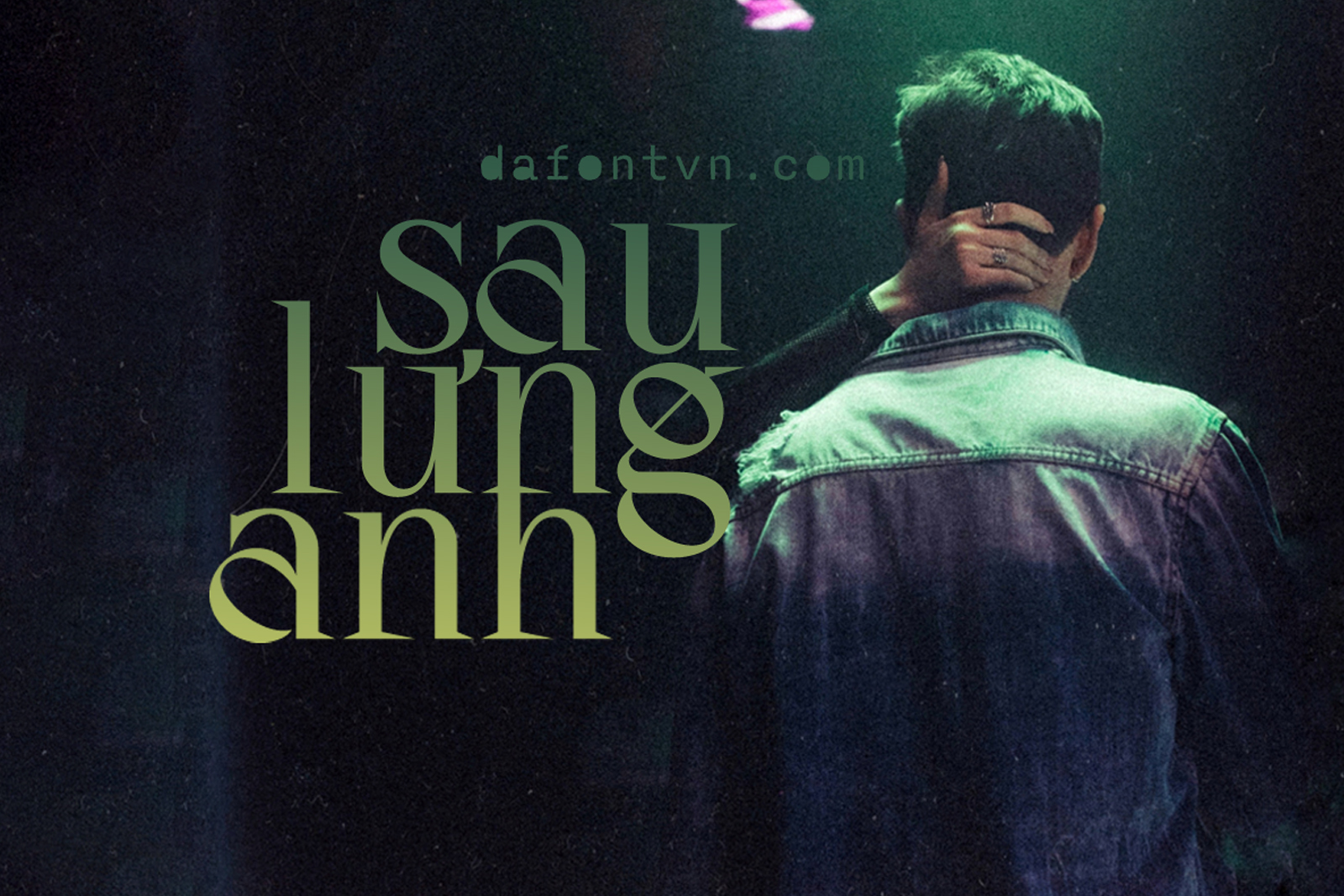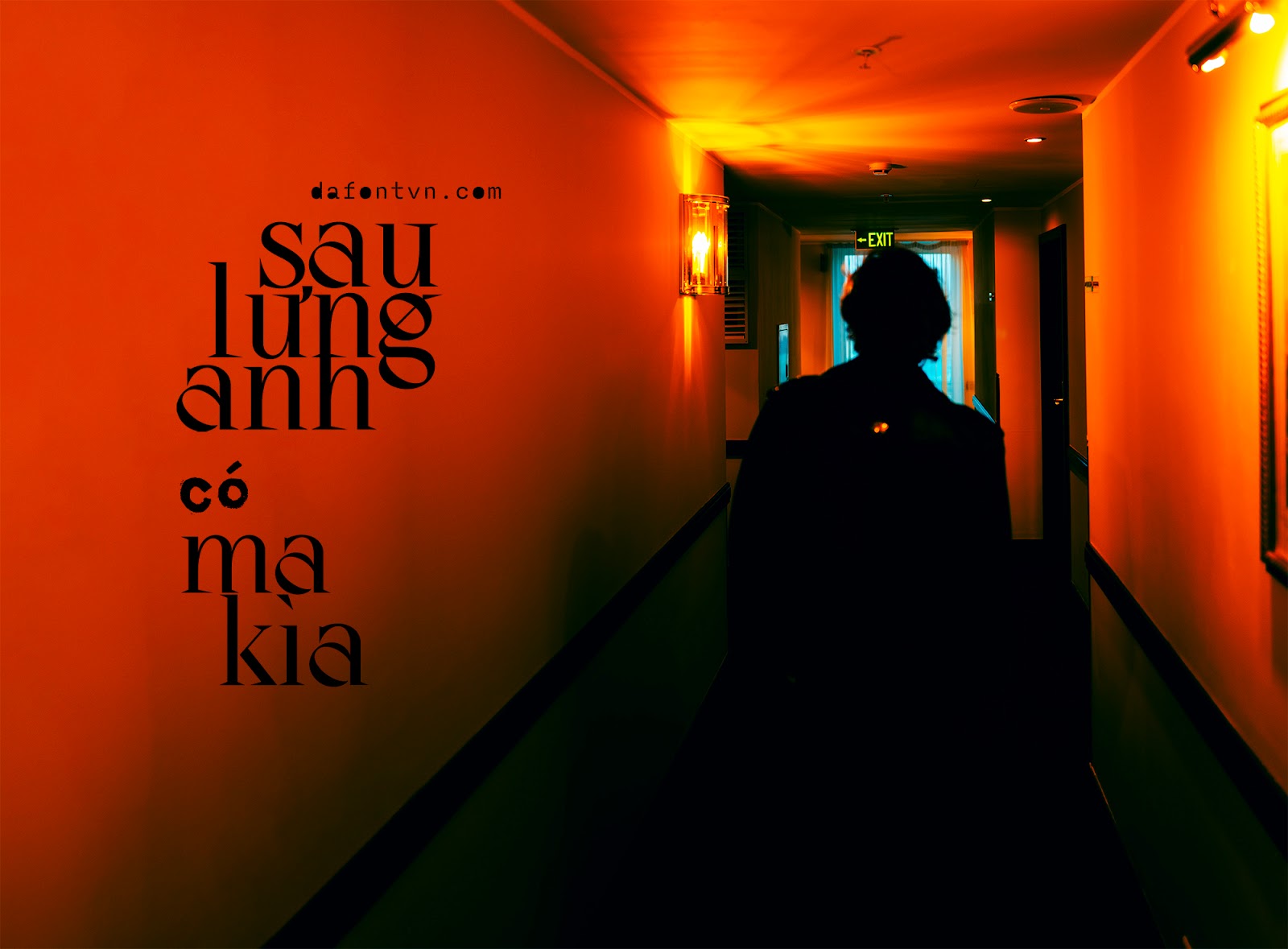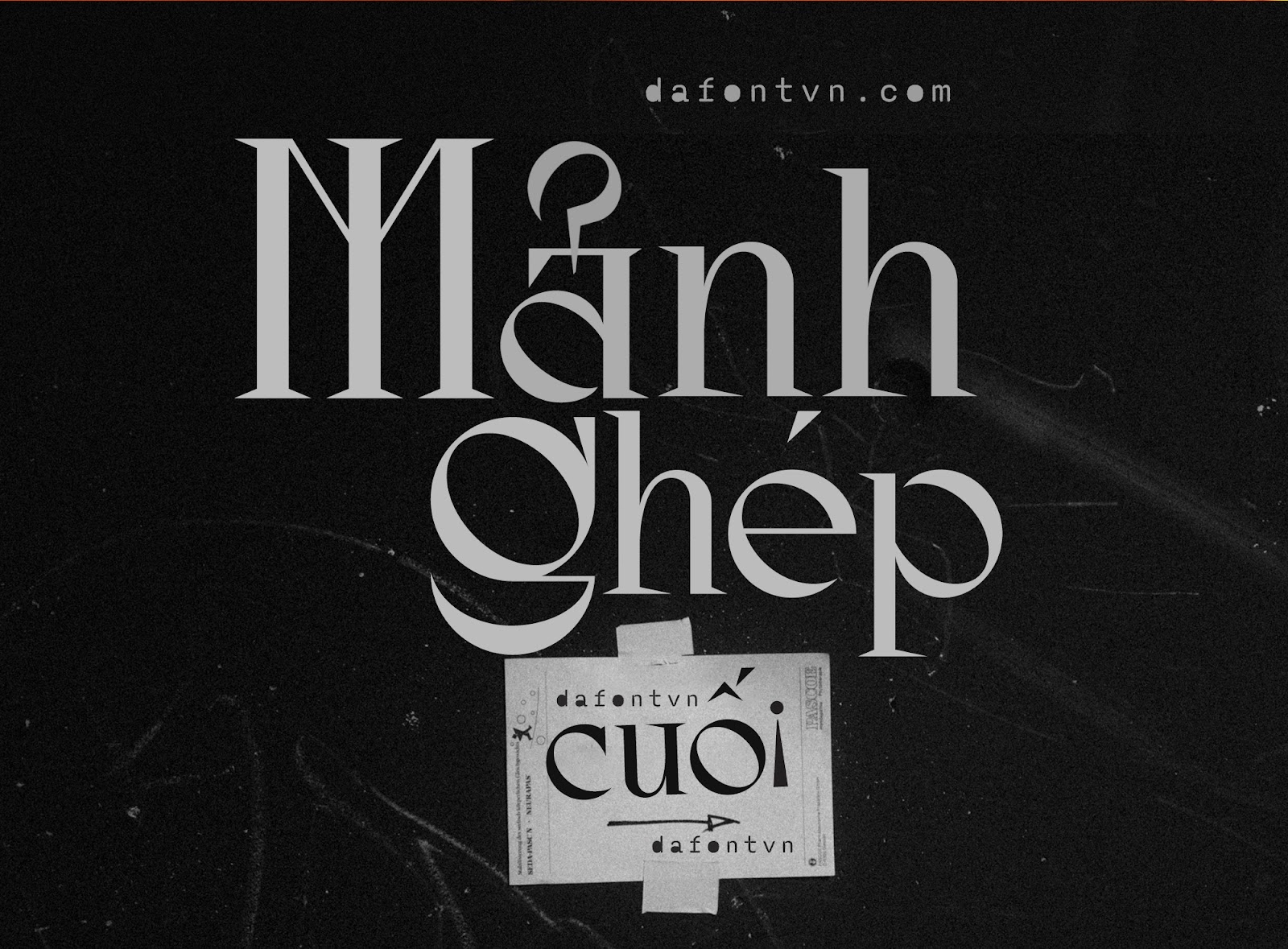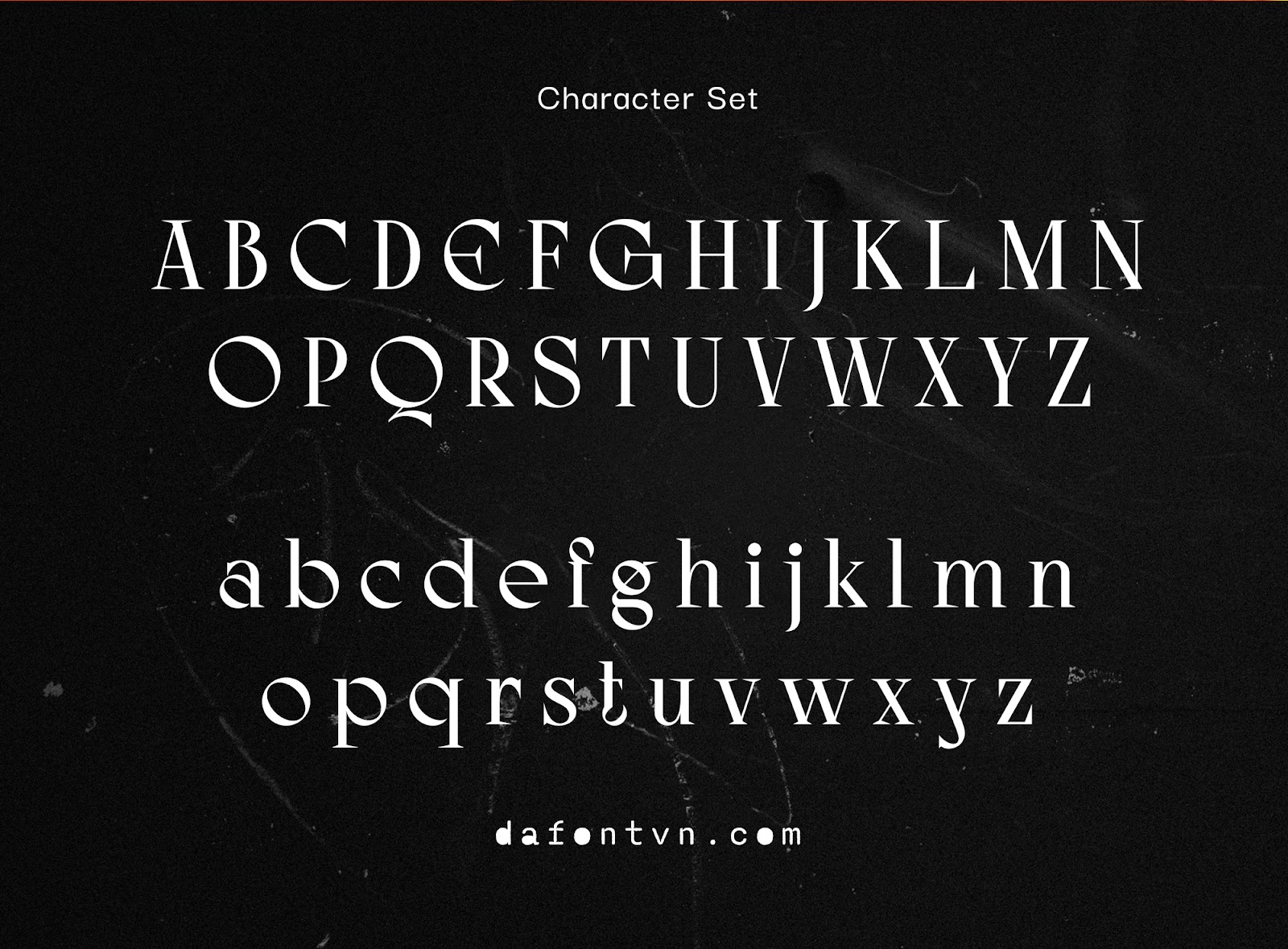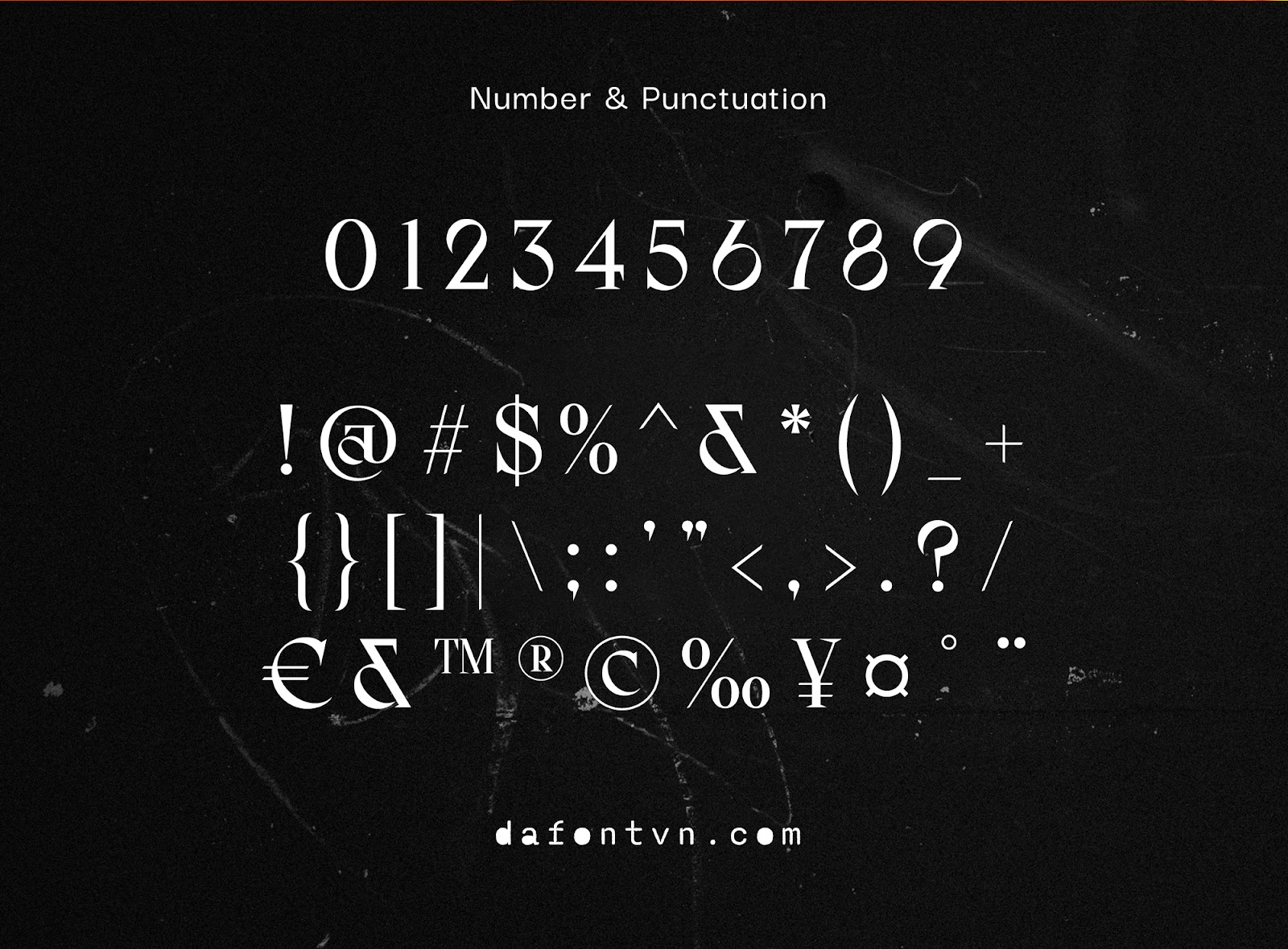
Font việt hóa AO Mireille – Display Typeface
AO Mireille – Display Typeface là một phông chữ hiện đại và sang trọng với các đường nét cứng cáp nhưng lại mang một vẻ đẹp quyến rũ và đẹp mắt. Bạn có sử dụng nó cho nhiều dự án thiết kế khác nhau như thiệp mời, typography, bìa sách, poster… Những thiết kế cần một font chữ hiển thị hiện đại và độc đáo.
Font AO Mireille việt hóa đầy đủ, kerning, chỉnh sửa lại một số đường nét của font và dấu được vẽ lại cũng như tối ưu hóa để sử dụng trên tất cả các phần mềm thiết kế khác nhau.
Font việt hóa AO Mireille - Display Typeface
Font AO Mireille việt hóa
AO Mireille - Display Typeface Font việt hóa siêu đẹp
AO Mireille Font - Character
AO Mireille Font - Number